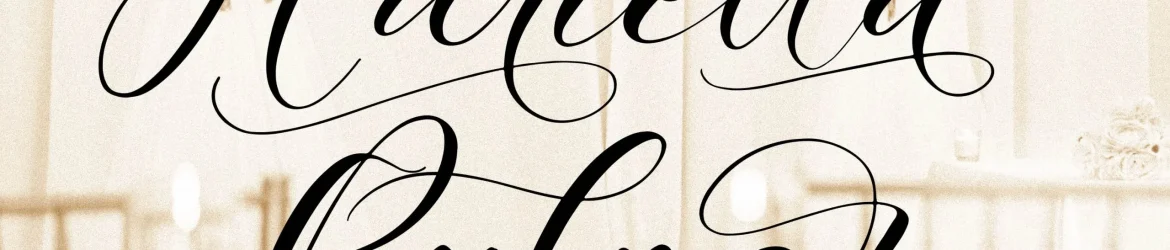
Harietta Bulmer Font – Download Grátis
A fonte ‘Harietta Bulmer’ é uma elegante escolha para quem deseja adicionar uma pitada de romantismo a qualquer projeto. Inspirada na arte do cógigo, esta fonte escrita foi projetada para um uso versátil que vai desde criar logos e estilos de marca até design de móveis de casa, embalagens de produtos, estampas em tênis, materiais promocionais como cartazes, nome cards, convites, cartões de agradecimento, etiquetas, capas de livros e tudo mais que deseje dar um toque delicado e elegante. Suas linhas fluidas se adaptam a diversos usos, tornando-a uma fonte indispensável para designers atentos às nuances da estética gráfica no Brasil.